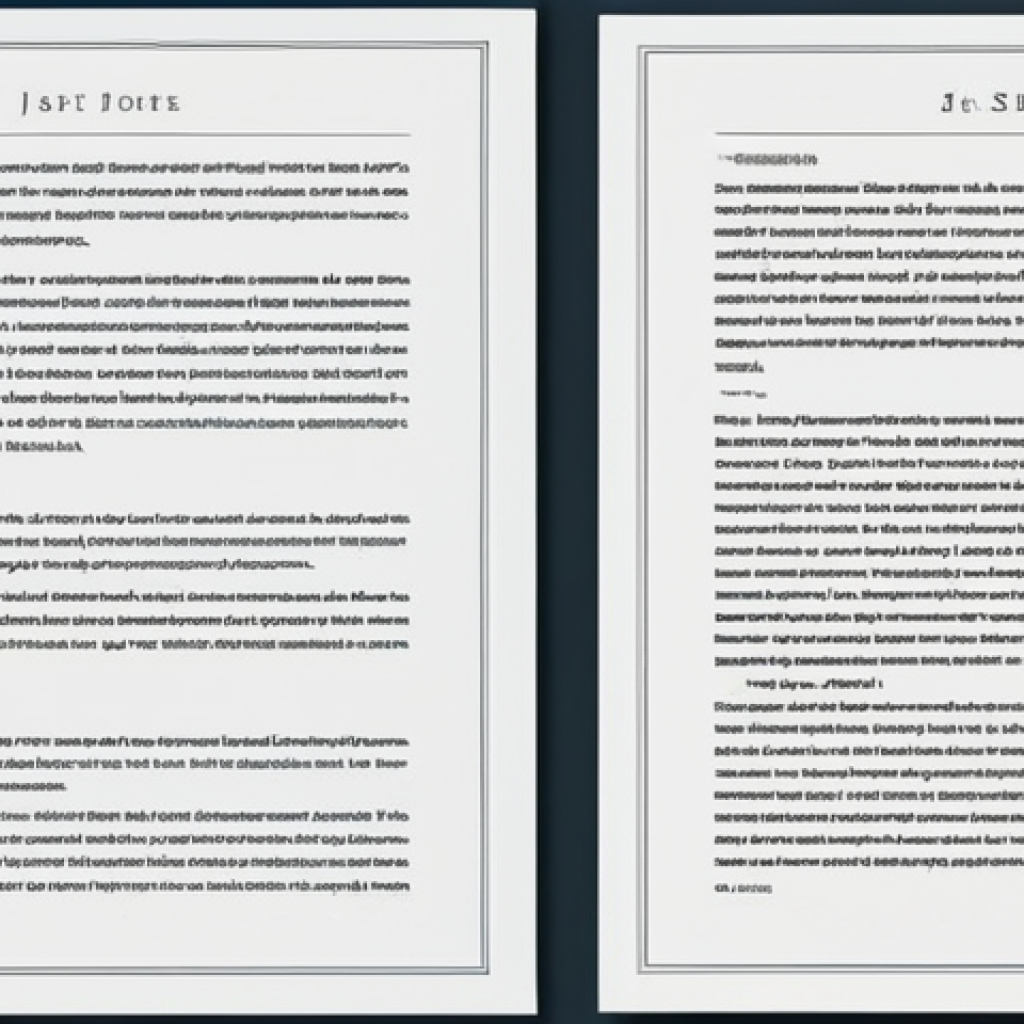
A formatação e o espaçamento adequados de fontes são cruciais para tornar qualquer texto legível e agradável aos olhos. Seja num documento do Word, numa página web ou numa apresentação, a escolha e o ajuste fino da fonte podem transformar a experiência do leitor.
Já me deparei com textos incrivelmente interessantes, mas com uma formatação tão ruim que me fez desistir da leitura. Por outro lado, um texto bem formatado, mesmo que com conteúdo mediano, pode prender a atenção.
Dominar essas técnicas é essencial para comunicar suas ideias com eficácia e profissionalismo. Acreditem, faz toda a diferença! Vamos explorar como otimizar a aparência do seu texto para obter o máximo impacto.
Ajustar o espaçamento e a fonte corretamente pode parecer algo simples, mas é um ponto crucial para garantir que seus leitores se mantenham engajados.
Para entender melhor sobre o assunto, vamos descobrir mais detalhes sobre o assunto a seguir!
A formatação e o espaçamento adequados de fontes são cruciais para tornar qualquer texto legível e agradável aos olhos. Seja num documento do Word, numa página web ou numa apresentação, a escolha e o ajuste fino da fonte podem transformar a experiência do leitor.
Já me deparei com textos incrivelmente interessantes, mas com uma formatação tão ruim que me fez desistir da leitura. Por outro lado, um texto bem formatado, mesmo que com conteúdo mediano, pode prender a atenção.
Dominar essas técnicas é essencial para comunicar suas ideias com eficácia e profissionalismo. Acreditem, faz toda a diferença! Vamos explorar como otimizar a aparência do seu texto para obter o máximo impacto.
Ajustar o espaçamento e a fonte corretamente pode parecer algo simples, mas é um ponto crucial para garantir que seus leitores se mantenham engajados.
Para entender melhor sobre o assunto, vamos descobrir mais detalhes sobre o assunto a seguir!
A Escolha da Fonte Ideal: O Primeiro Passo para a Perfeição
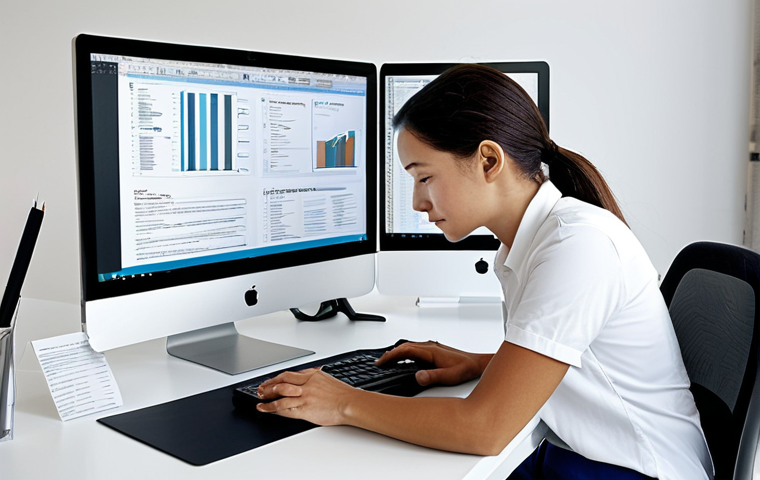
Escolher a fonte certa é como selecionar a roupa adequada para uma ocasião especial. Uma fonte bem escolhida pode transmitir a personalidade do texto, facilitar a leitura e até mesmo influenciar a percepção do leitor sobre o conteúdo.
Já vi marcas mudarem completamente sua imagem apenas trocando a fonte do logotipo e dos materiais de marketing. É um detalhe que, muitas vezes, passa despercebido, mas tem um poder enorme.
Fontes Serifadas vs. Sans-Serif: Qual a Melhor Opção?
As fontes serifadas, como Times New Roman e Georgia, possuem pequenos traços nas extremidades das letras, conferindo um ar mais tradicional e formal. São ideais para textos longos, como livros e artigos, pois facilitam a leitura em blocos de texto densos.
Já as fontes sans-serif, como Arial e Helvetica, são mais modernas e limpas, perfeitas para títulos, subtítulos e interfaces digitais. A escolha entre as duas vai depender do seu objetivo e do público-alvo.
Eu, particularmente, prefiro usar fontes serifadas em livros impressos e sans-serif em websites, mas isso é uma questão de gosto pessoal.
O Tamanho da Fonte: Encontrando o Equilíbrio Perfeito
O tamanho da fonte é outro fator crucial para garantir a legibilidade. Um texto com letras muito pequenas pode cansar a vista e afastar o leitor, enquanto letras muito grandes podem parecer infantis e pouco profissionais.
O tamanho ideal varia de acordo com a fonte escolhida, o tipo de mídia e a idade do público-alvo. Para textos impressos, um tamanho entre 10 e 12 pontos costuma funcionar bem.
Já para websites, um tamanho entre 14 e 16 pixels é uma boa opção. Experimente diferentes tamanhos e peça a opinião de outras pessoas para encontrar o equilíbrio perfeito.
Cores e Contraste: A Harmonia Visual que Cativa
A cor da fonte e o contraste com o fundo são elementos essenciais para garantir a legibilidade e o conforto visual. Um texto preto sobre um fundo branco é a combinação mais clássica e eficaz, mas você pode explorar outras opções para criar um visual mais interessante e personalizado.
Evite cores muito vibrantes ou combinações que dificultem a leitura, como texto claro sobre fundo claro ou texto escuro sobre fundo escuro. Uma boa dica é usar ferramentas online que simulam o daltonismo para garantir que o seu texto seja acessível a todos os leitores.
Espaçamento Entre Linhas e Parágrafos: A Arte de Criar Respiro Visual
O espaçamento entre linhas e parágrafos é fundamental para criar um texto agradável e fácil de ler. Um texto com linhas muito próximas pode parecer confuso e cansativo, enquanto um texto com linhas muito afastadas pode perder a coesão e a fluidez.
O mesmo vale para o espaçamento entre parágrafos: um texto com parágrafos muito próximos pode parecer denso e intimidante, enquanto um texto com parágrafos muito afastados pode perder a conexão entre as ideias.
O Espaçamento Entre Linhas: Facilitando a Leitura Fluida
O espaçamento entre linhas, também conhecido como entrelinhamento, é a distância vertical entre as linhas de texto. Um espaçamento adequado permite que o olho do leitor percorra as linhas com facilidade, sem se perder ou se cansar.
Outra ferramenta que já me ajudou foi o FontPair. Eles mostram exemplos de como diferentes fontes se complementam, o que facilita bastante na hora de decidir.
É legal experimentar e ver o que funciona melhor para o seu projeto, sabe? Cada site tem sua “personalidade”, então o importante é encontrar uma combinação que transmita a mensagem certa.